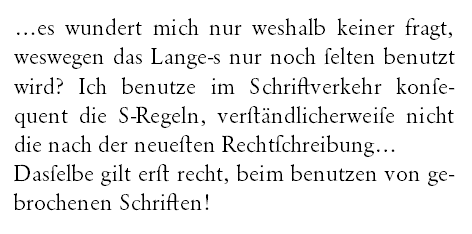
Die Diskuſſion zum ß ist ja sehr intereſſant, aber müßte man konſequenterweiſe nicht nur ein Verſal-ß, sondern auch ein Lang-s (ſ) in der Antiqua und ein Verſal-J in der Fraktur einführen? Alle diese Zeichen ſind für eine eindeutige Worterkennung notwendig.
Klar, alle dieſe Zeichen ſind nicht unbedingt notwendig und würden mangels notwendiger Tastaturlayouts am Computer ſich eh nie durchſetzen. Man ſchau ſich nur mal das @ an. Obwohl heute am PC ein ſtändig genutztes Zeichen, versteckt es ſich auf der PC-Taſtatur noch immer hinter dem Fingerbrecher ALT+Q und beim MAC gar abweichend unter ALT+L. Kein Menſch hingegen bräuchte das ^ als Taſte. Man könnte dieſe Taſte bei PC und MAC weltweit problemlos für das @ nutzen, nur macht es niemand. Ich bezweifel daher, daß ſich ein Verſal-ß im elektroniſchen Bereich durchſetzen könnte, denn eine eigene Taste (UMSCH+ß) wird es nicht bekommen.
Aber wenn wir ſchon bei wünſchenswerten Ergänzungen ſind, ſo möchte ich mich für die Einführung eines Lang-s (ſ) in der Antiqua ausſprechen. Im Deutſchen, welche wie keine andere Sprache S-Laute am Anfang und Ende von Wörtern einſetzt und dieſe beſonders durch Wortzusammenſetzungen auch noch aneinanderfügt, wäre ein Lang-s eine wirkliche sinnvolle Leſehilfe. Egal ob alte oder neue Rechtſchreibung. Ich perſönlich verwende ſeit kurzem das Lang-s in meiner Schreibſchrift. Es ſieht aus wie ein Druck-Antiqua f ohne Querstrich. Ferner ſchreibe ich das kleine z wie in Sütterlin mit Schlaufe, da das ein ſchöneres Schriftbild ergibt. Und als nette perſönliche Note ſchreibe ich das ß als handſchriftliche Ligatur aus Lang-s und Rund-z.
Zitat Wikipedia zum Lang-s:
"In diesen Fällen ist Aussprache und Bedeutung abhängig davon, ob das s im Auslaut oder im Anlaut steht. Daher kann die Differenzierung zwischen ſ und s für den Leser von besonderem Vorteil sein. Beispiel: Durch Verwendung des langen ſ ist es auch ohne Kontext sofort klar, ob eine Wachſtube (Wach-Stube) oder eine Wachstube (Wachs-Tube) gemeint ist. Weitere Beispiele: Kreiſchen (Krei-schen, für Schreien) oder Kreischen (Kreis-chen, für kleiner Kreis), Verſendung (Ver-sendung) oder Versendung (Vers-Endung), Röschenhof (Rös-chen-hof, von kleine Rose) oder Röſchenhof (Rösch-en-hof, vom Eigenname Rösch)."
PS: man möge mir bitte Tippfehler mit dem ſ nachſehen, ich bin Neuling in deſſen Verwendung
Nicht uninteressant was du schreibst. Allerdings bin ich doch mitten im Lesen ausgestiegen. Wie wir alle bin ich auf das Lesen von Wortbildern konditioniert und habe es als mühsam empfunden plötzlich über kleine s mit Oberlänge zu stolpern. Und irgendwie hatte ich das Gefühl beim Lesen zu lispeln – aber wie gesagt: ich habe mich bisher mit der Thematik nicht befasst.
Komisch, mir selbst macht das eigentlich keine Probleme. Vielleicht liegt das daran, daß ich viele Bücher in Fraktur gelesen habe und an die 4 S-Laute auch im Schriftbild gewöhnt bin. Viel problemtischer ist für mich die Nur-Kleinschreibung und fehlende interpunktion bei Chats und SMS. Da werde ich hippelig und breche das Lesen hin und wieder ab.
man solle schon unterscheiden ob es sich um einen schnell geschrieben, kleinen text handelt (sm, chat, mail) oder um komplette bücher et cetera.
ich denke das sich mehr leser an eine "nur kleinschreibung" gewöhnen könnten, im gegenteil zum langen "ſ". schon allein deshalb weil viele auch englisch können, dort wird ja zu 80 % auch alles klein geschrieben.
man solle schon unterscheiden ob es sich um einen schnell geschrieben, kleinen text handelt (sm, chat, mail) oder um komplette bücher et cetera.
Zweifellos richtig. Nur unterscheiden die Schreiber heutzutage eben oft nicht mehr, was mühsam ist.
ich denke das sich mehr leser an eine "nur kleinschreibung" gewöhnen könnten, im gegenteil zum langen "ſ".
Es ist empirisch erwiesen, daß ein abwechslungsreiches Schriftbild mit vielen Ober- und Unterlängen den Lesefluß positiv beeinflußt. Sprich: man kann schneller und müheloser auch längere Texte lesen. Hier das Englische als Beispiel zu nehmen ist unsinnig, wo doch die durchschnittliche Wortlänge zwischen diesen beiden Sprachen kaum unterschiedlicher sein kann. Deutsch mit seinen langen zusammengesetzten Wörtern ist ganz besonders stark auf die Fähigkeit der Leser angewiesen, Wörter nicht zu buchstabieren, sondern am Schriftbild zu erkennen. Das Lang-s ist hier hilfreich, wenn auch für Fraktur-Ungeübte eine Eingewöhnungszeit nötig ist. Außerdem rege ich das lange s ja nicht als verpflichtend an.
PS: Übrigens gab es das Lang-s auch ursprünglich bei unseren westlichen europäischen Nachbarn - es wäre daher sogar internationaler als unser ß.
Hallo Maetsch,
es verbietet Dir niemand das lange s zu verwenden. Hier im Forum wirst Du kaum Leute damit provozieren können. Eine gut ausgebaute OpenType Schrift bietet immer öfter auch ein langes s mit den entsprechenden Ligaturen.
Wie wir alle bin ich auf das Lesen von Wortbildern konditioniert und habe es als mühsam empfunden plötzlich über kleine s mit Oberlänge zu stolpern. Und irgendwie hatte ich das Gefühl beim Lesen zu lispeln
Genau das passiert mir beim Lesen des ersten Beitrags der aktuellen Signa über das Versal-ß. Es ist ungewohnt und damit mühsam. Zudem habe ich noch nicht eruieren können warum das langs verwendet wird, oder ob es "nur" eine Laune des Autors ist. Und demzufolge weiß ich nicht ob ich es gutheißen soll. Wenn es keinen Grund gibt, lenkt es nur vom Thema ab.
(das ganze ist jetzt kein Vorwurf, sondern eher eine Frage nach dem Warum)